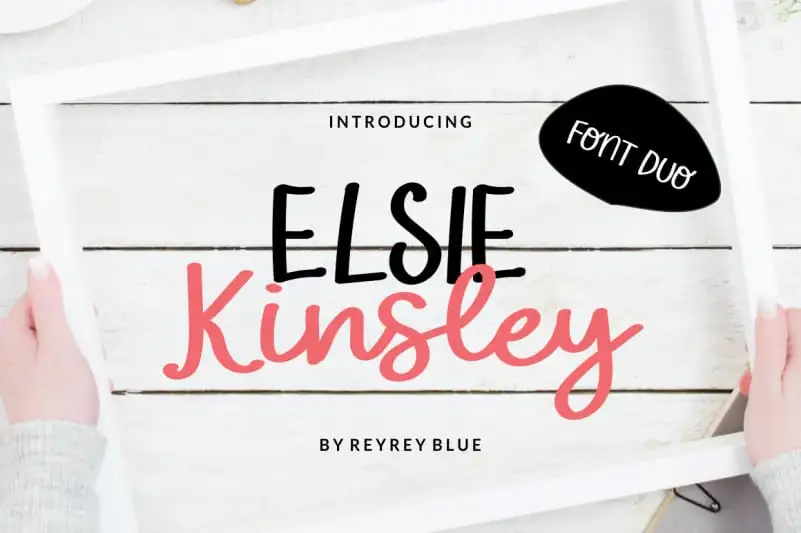
Elsie Kinsley Display Font Duo – Download Grátis
Introduzimos Elsie Kinsley Display Font Duo, uma linda dupla de fontes que mantêm um estilo leve e moderno. Esta fonte vem com duas fontes escritas a mão para dar ao seu design um toque único e divertido. Ideal tanto para trabalhos tipográficos como para criações de marca, websites, materiais de merchandising, embalagens, citações, convites e mensagens de felicitação, Elsie Kinsley Display Font Duo é uma escolha perfeita. Seja você um designer gráfico ou criador de conteúdo online, pode explorar inúmeras maneiras em que essa fonte pode adicionar a sua identidade visual. Ideal tanto para pessoas que gostam de letras curvas e delicadas quanto aqueles que buscam algo mais moderno e divertido, Elsie Kinsley Display Font Duo é uma excelente opção para qualquer projeto de design. Com certeza vai enriquecer seus projetos, dando-lhes um toque único e autêntico.